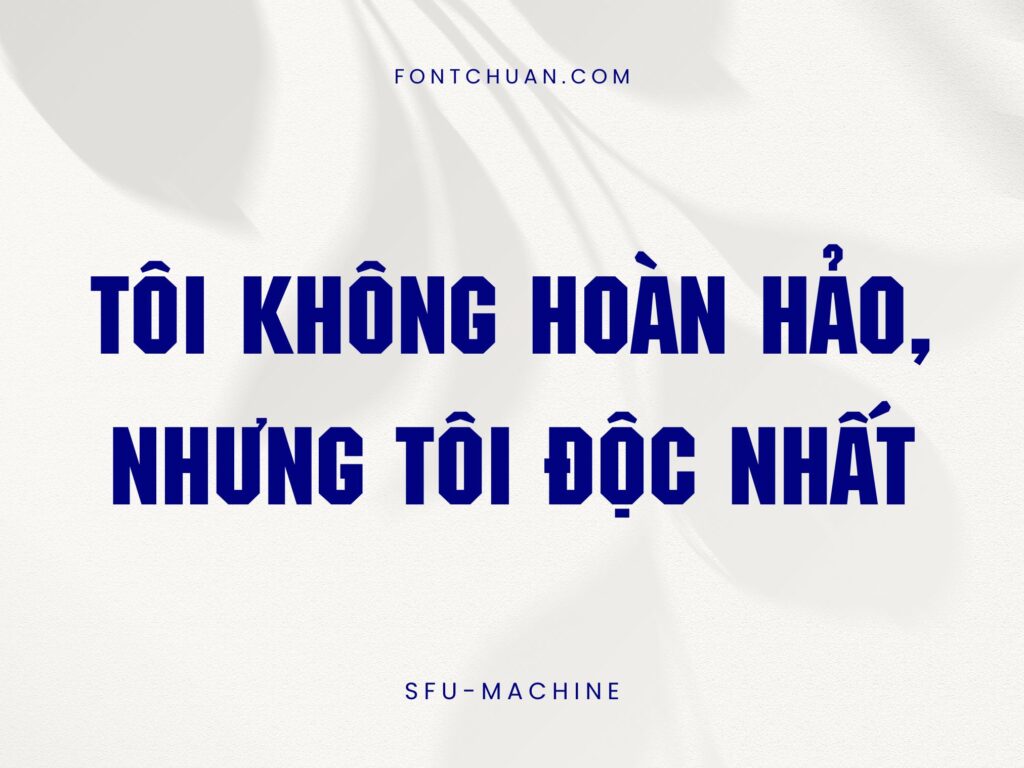
Machine là một Font Sans serif được thiết kế với phong cách công nghiệp và hiện đại. Font này được sưu tầm và đăng bởi thành viên của Font Chuẩn. Với thiết kế mạnh mẽ và góc cạnh, Machine không chỉ tạo cảm giác công nghiệp mà còn rất phù hợp làm Font logo cho các thương hiệu công nghệ hoặc các dự án cần sự hiện đại và khác biệt.
Về mặt thiết kế, Machine có các đường nét dày và góc cạnh, tạo cảm giác mạnh mẽ và hiện đại. Font này hỗ trợ nhiều ngôn ngữ và bao gồm các ký tự đặc biệt, giúp người dùng dễ dàng tùy chỉnh theo nhu cầu. Machine thường được sử dụng trong các thiết kế liên quan đến công nghiệp, công nghệ, và các dự án cần sự mạnh mẽ và hiện đại. Các ngành nghề như công nghệ, quảng cáo, và thiết kế đồ họa có thể tận dụng kiểu chữ này để tạo dấu ấn đặc biệt trong truyền thông.